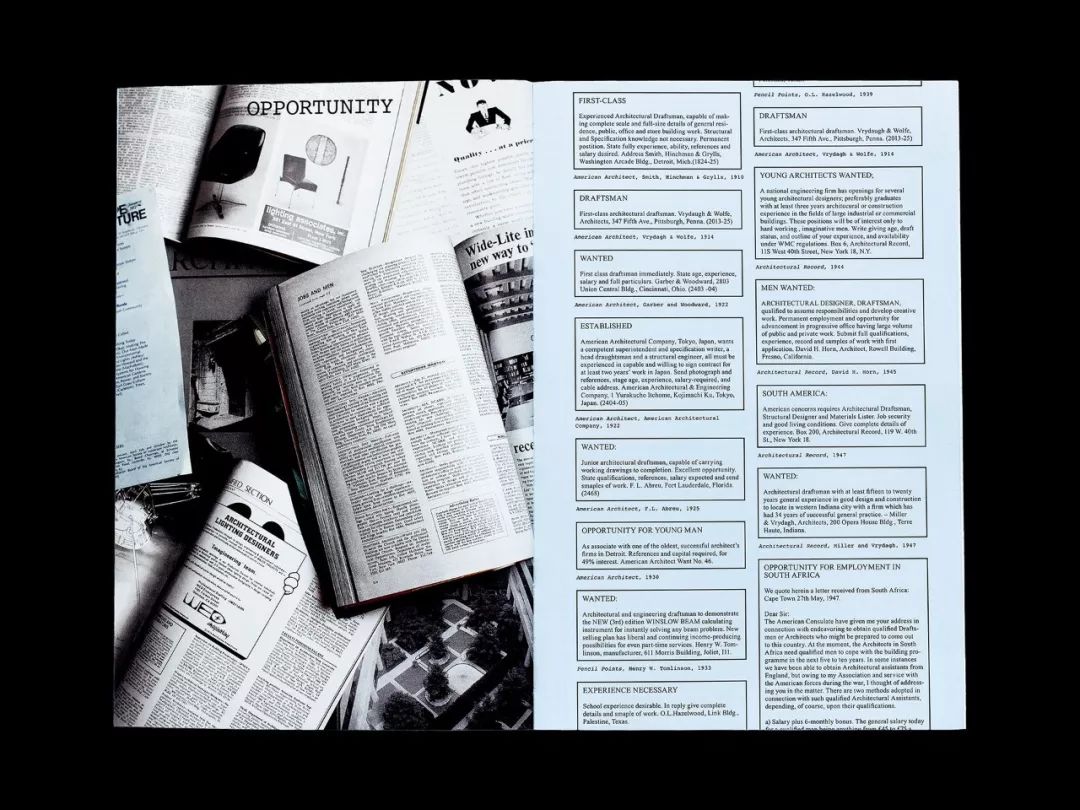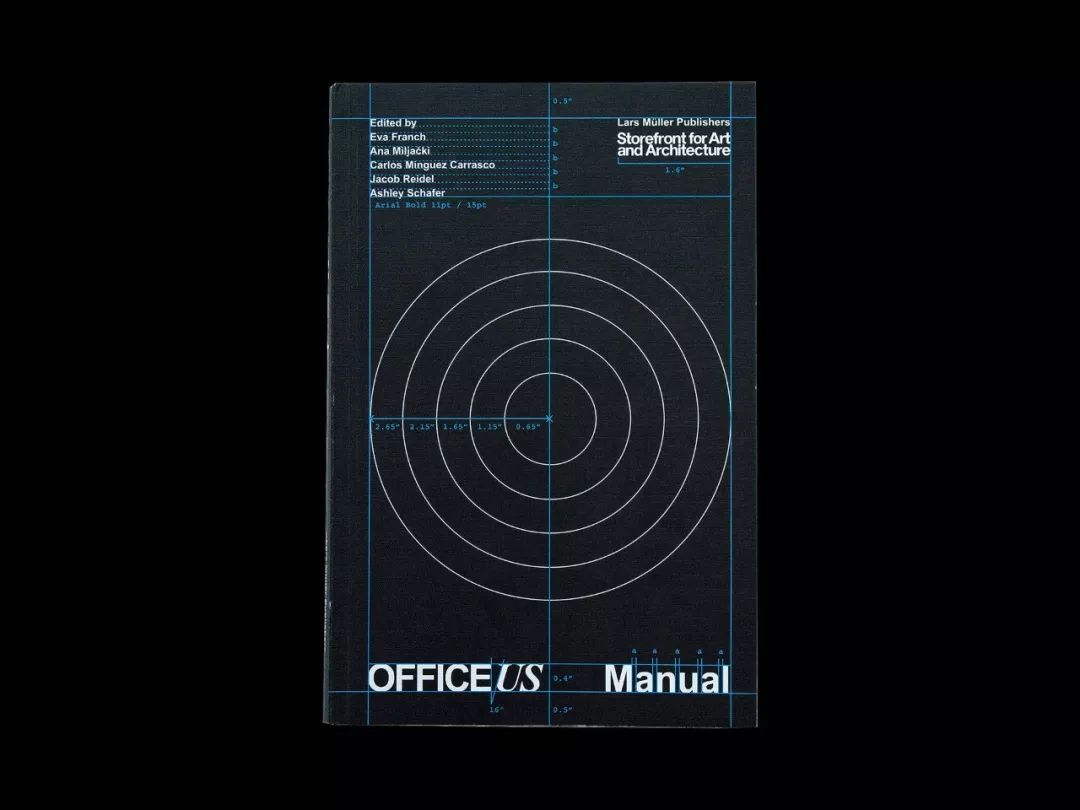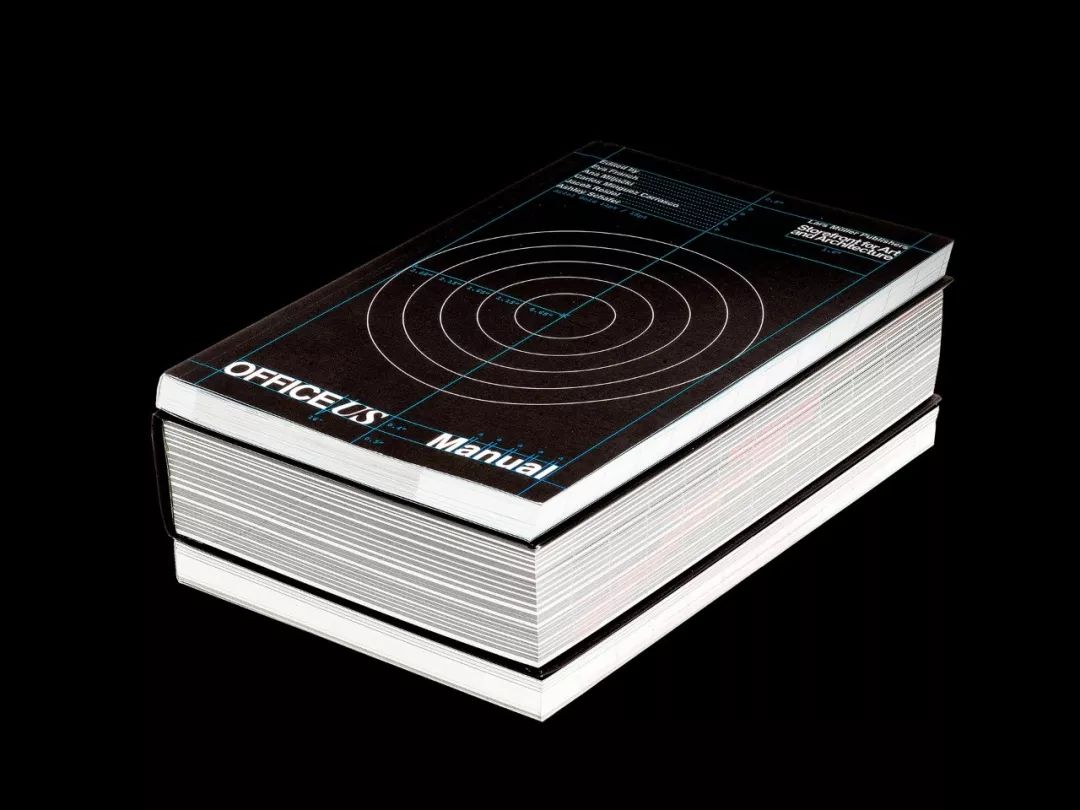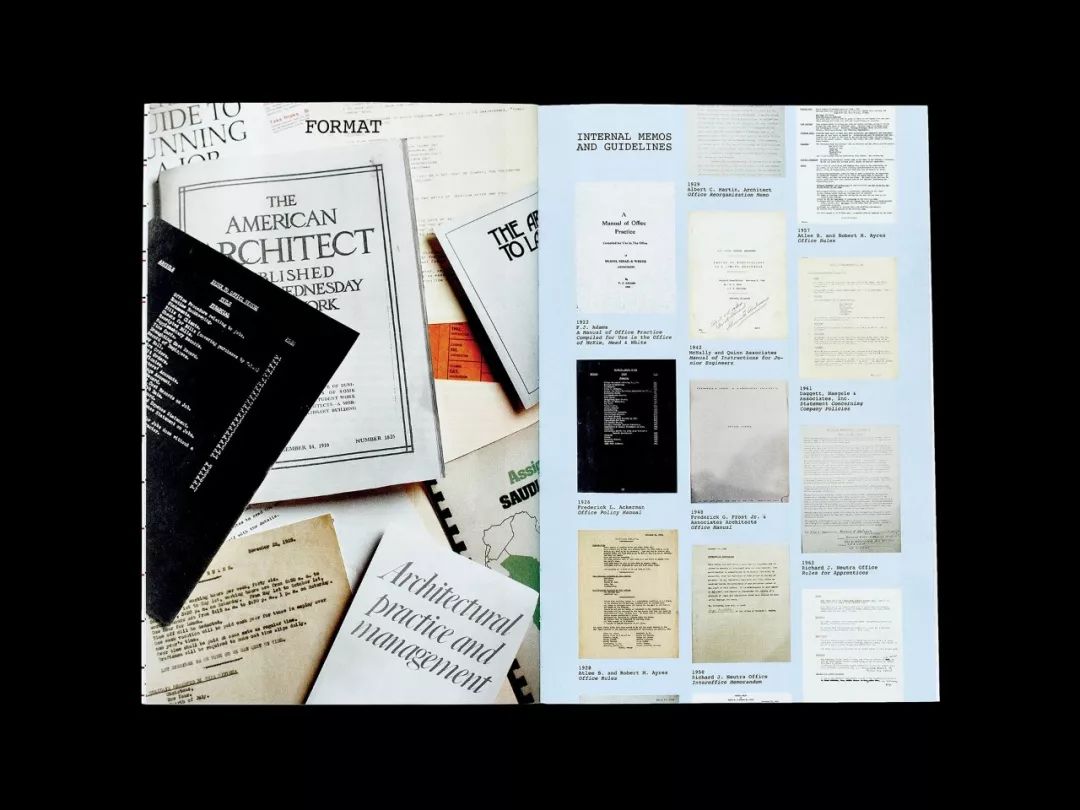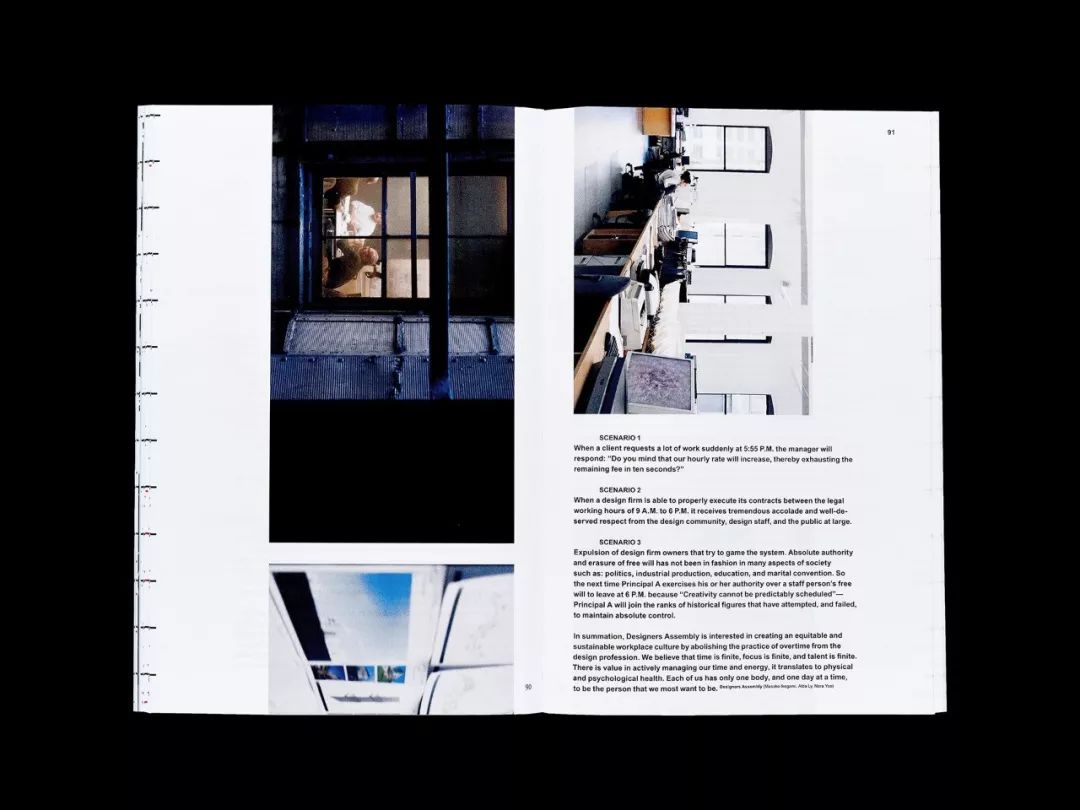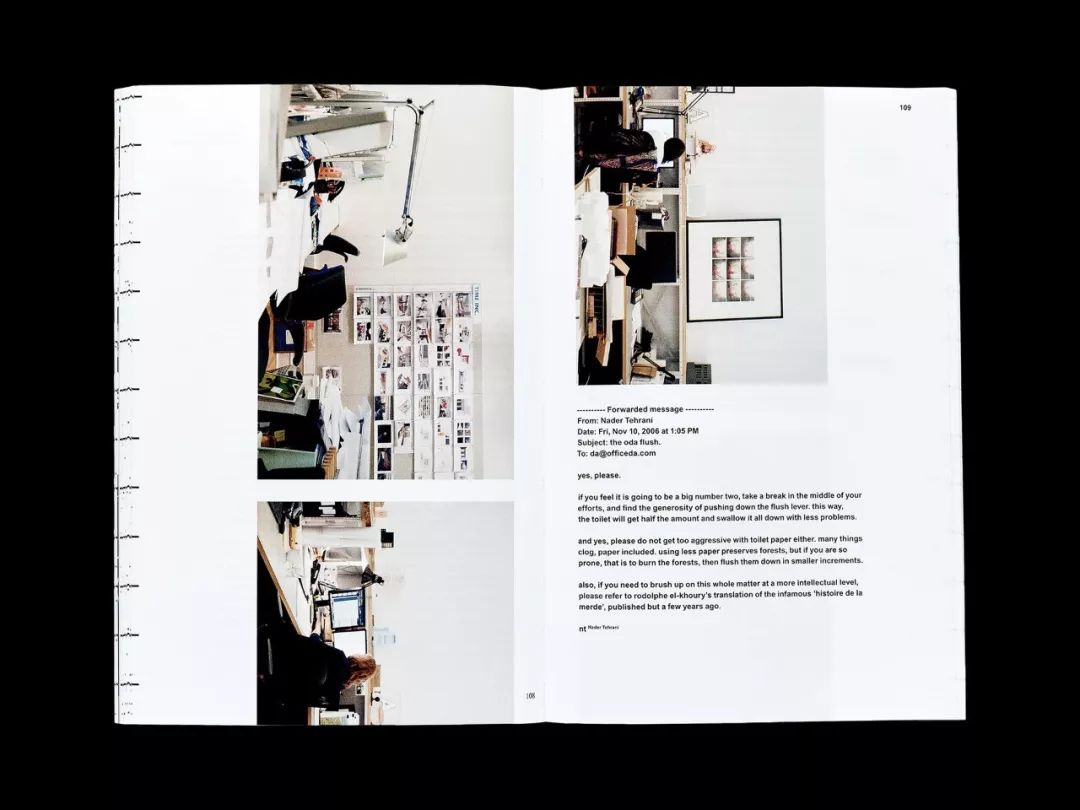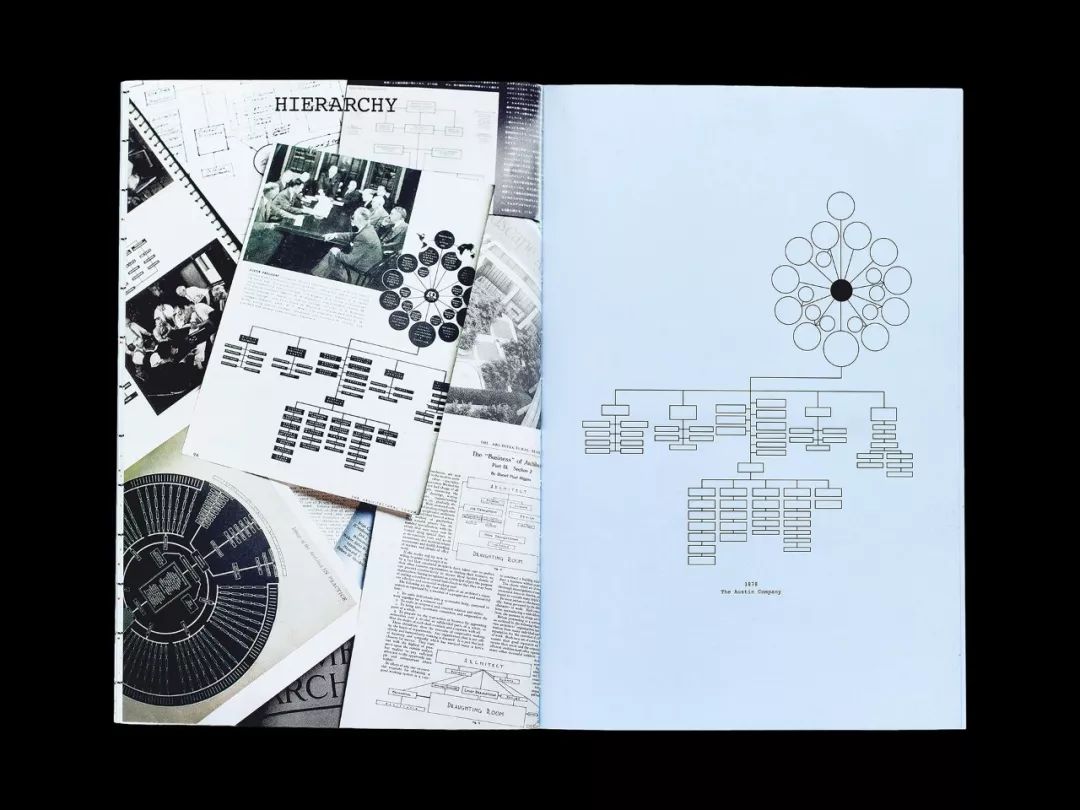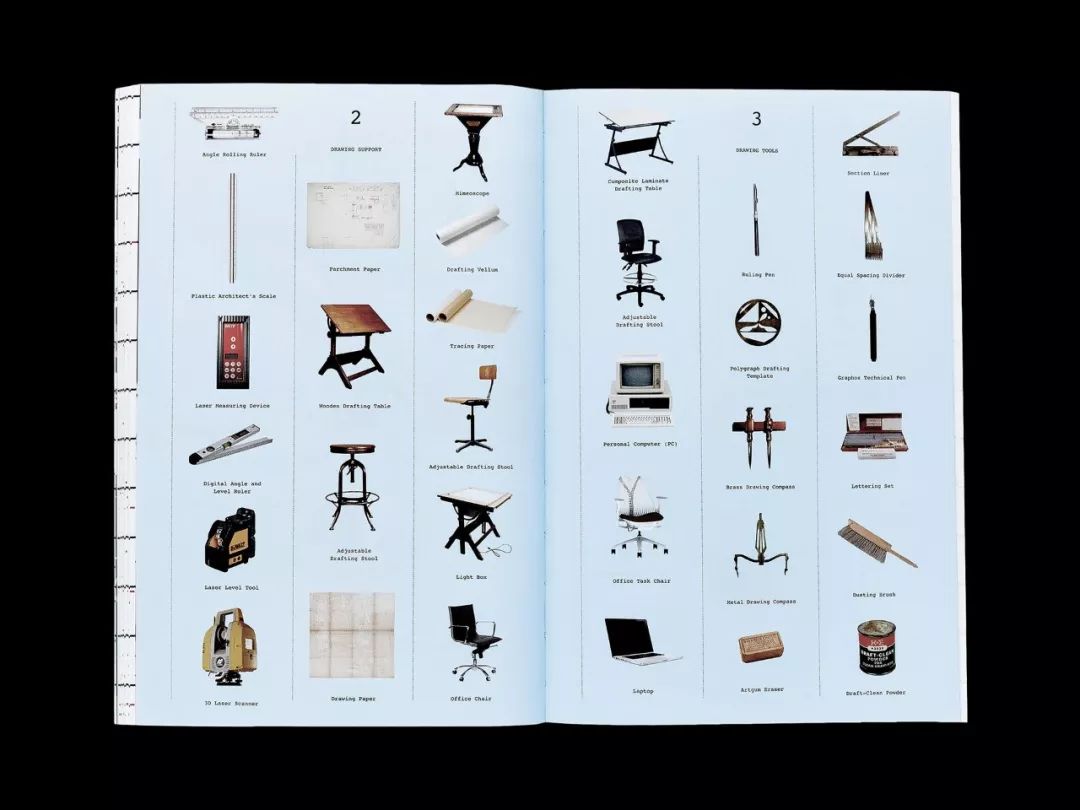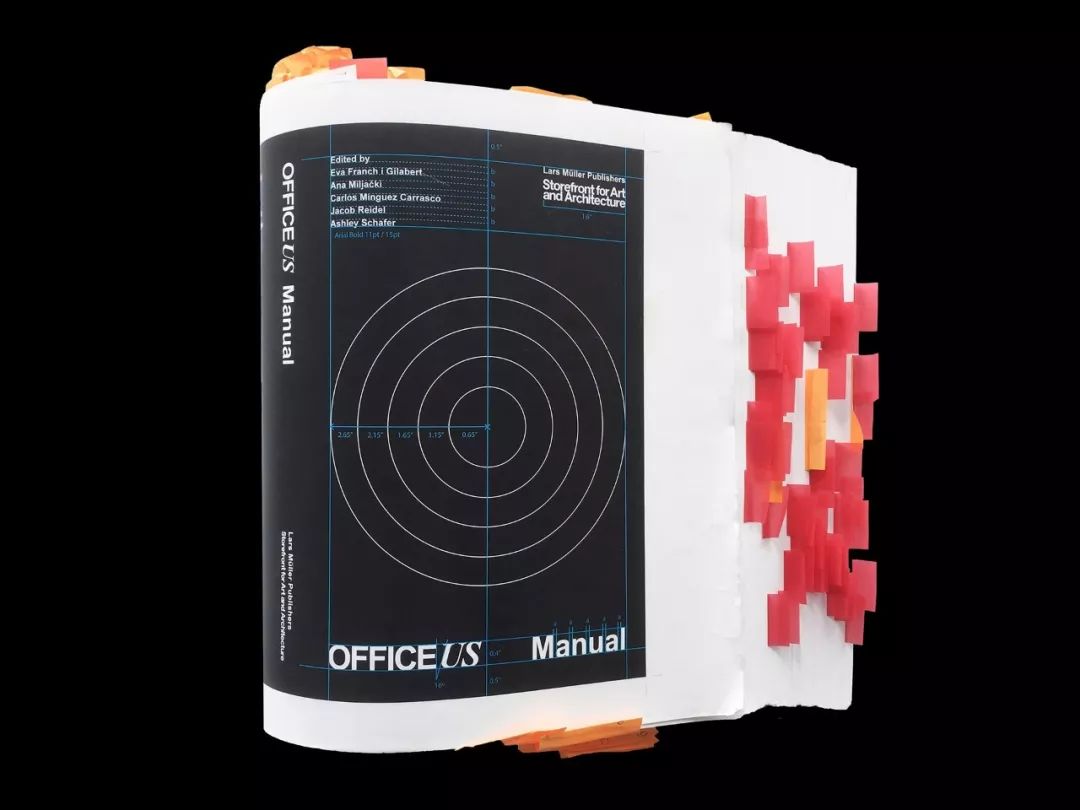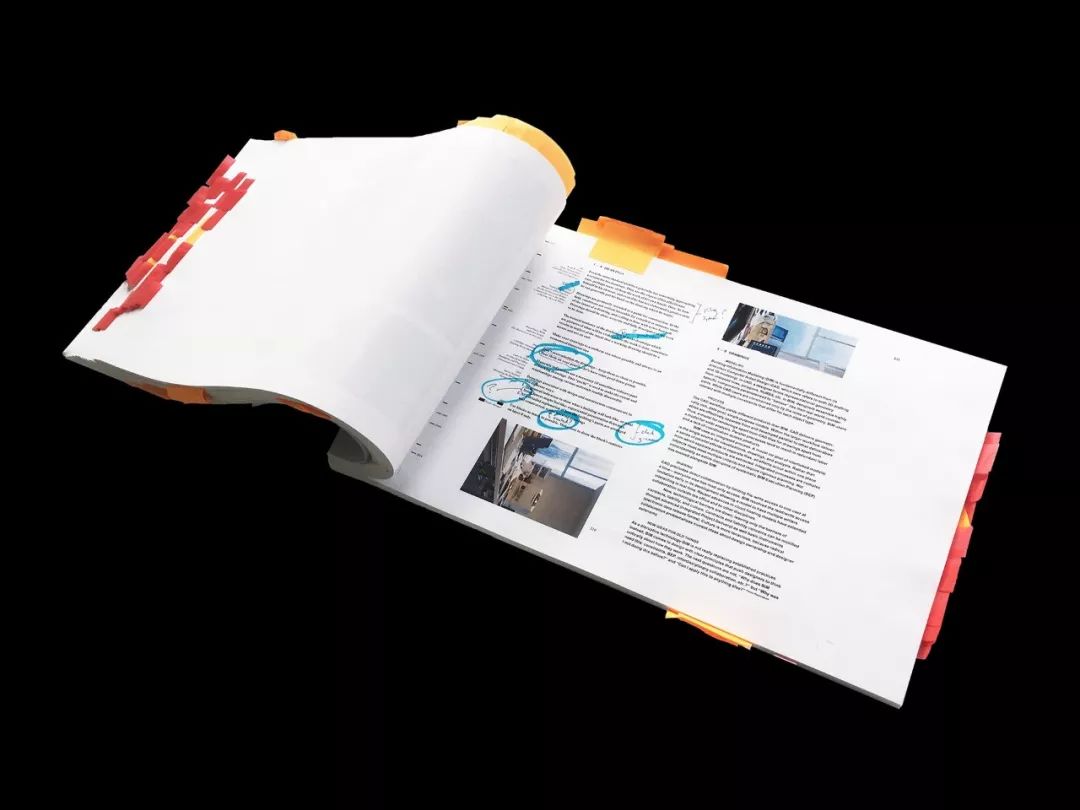
Natasha Jen(任黛珊)1976年出生于台北市,在纽约的视觉艺术学院(The school of visual arts in new york city)学习平面设计,于2002年在那里拿到了她的艺术学士学位。在2010年建立她的个人工作室之前,Natasha Jen 曾经在 Base Design、2×4, inc.和 Stone Yamashita Partners 工作过。
Natasha Jen 说到,“我认为我的角色是在与文字、符号及图像一起玩耍的过程中,让一些无形的事物变得真实可感,又或者让一些抽象的事物变得易于理解。如果在这个基础上,最终设计出的产物又能够让人愉悦,那可能就是我们最大的愿望了。”
Jen 是一位多产的平面设计师,她为 Nike 和纽约时代广场等客户进行品牌、展览空间、装置以及其他各类设计工作。下面跟大家分享Natasha Jen的有关作品,在字里行间感受 Natasha Jen 对字体的热爱。
Natasha Jen为 活动设计了品牌,其中包括定制字体和充满活力的黄色,灵感来自于该地点。这本书记录了2016年在纽约艺术和建筑店面举办的“封闭世界”展览的研究成果, Pentagram的Natasha Jen将屡获殊荣的展览设计扩展到了Storefront与LarsMüller出版社合作出版的书中。
Pentagram的Natasha Jen和团队为2018年6月举办的第一届博览会设计了品牌标识。品牌以排版和矩形为中心,以书籍或建筑说话为侧面立面。形状可以堆叠和分层,形成各种不同的排列,包括形成“建筑”字母“A”的桩。团队为活动创造了各种各样的材料,包括动态图形和数据可视化。OfficeUS手册是美国建筑工作场所的指南,通过过去100年来建筑办公室的日常协议,政策和程序进行了记录。Natasha Jen的设计结构就像员工手册一样,编制了从工作列表,时间表和估算到工作站和接待区,办公时间和福利等各种指南。这本书非常有趣,因为它非常重要,因此可以深入了解建筑公司的办公室生活在过去一个世纪中的变化情况以及它保持不变的程度。
建筑师热爱书籍,艺术和建筑店面在5月7日纽约公共图书馆举办的2018年春季出版活动上庆祝了这种出版热情。Pentagram的Natasha Jen和他的团队为这次活动设计了身份和动作图形,以主题“lit”为中心。为了获得利益,黑白字体的运动场穿过一条亮红色的线,这条线暗示着一本书的阴沟。弧形的页面状曲线,类型创建了一个空间深度的错觉,并设置旋转在运动图形。
Khaore是限量版生产的新品牌精致皮革奢侈品。手提包和其他配饰被设想为“艺术与实用”,以精致的细节重新诠释了平凡的雕塑形式的平凡日常物品。Pentagram Natasha Jen和团队为该品牌设计了一个品牌标识,表达了其独特的主张。Pentagram的Natasha Jen为这本书设计了一个突出主题“实时订阅”,以图片和活动的时间线记录了2016-2017学年。